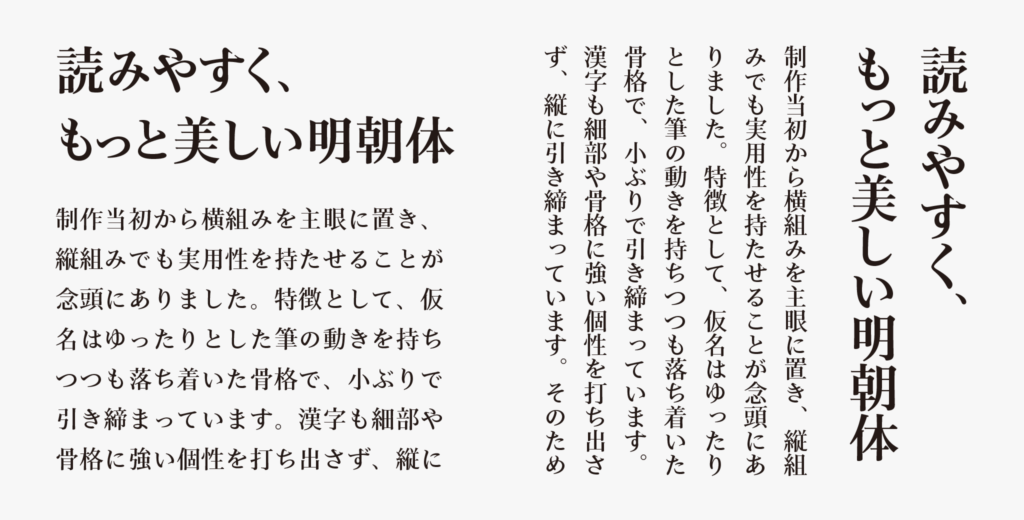
純明朝開発ストーリー1「骨格の特徴 その1」
純明朝・純明朝 ヘッドライン・純明朝 ヘアラインで漢字を担当した私は、仮名との関係や、どのような書体を目指すのか、書体の位置付け、新しいものにするにはどのような形になるのかを探りつつ制作を始めました。漢字筆画の細部ももちろんですが、それ以上に骨格に苦心しました。
制作当初から横組みを主眼に置き、縦組みでも実用性を持たせることが念頭にありました。特徴として、仮名はゆったりとした筆の動きを持ちつつも落ち着いた骨格で、小ぶりで引き締まっています。漢字も細部や骨格に強い個性を打ち出さず、縦方向に引き締まっています。
上記の特徴や大きさの比率によって、横組みでは漢字と仮名の固有の表情、仮名の脈絡や筆の動きが見えやすく、縦組みでは仮名と漢字がともに引き締まっているため縦方向に目が流れるようにラインが揃いフラットで、字面いっぱいの漢字を持った明朝体とは違う印象があります。それを特徴付けている引き締まった漢字の骨格をどのように制作していったか、次回の記事で紹介します。